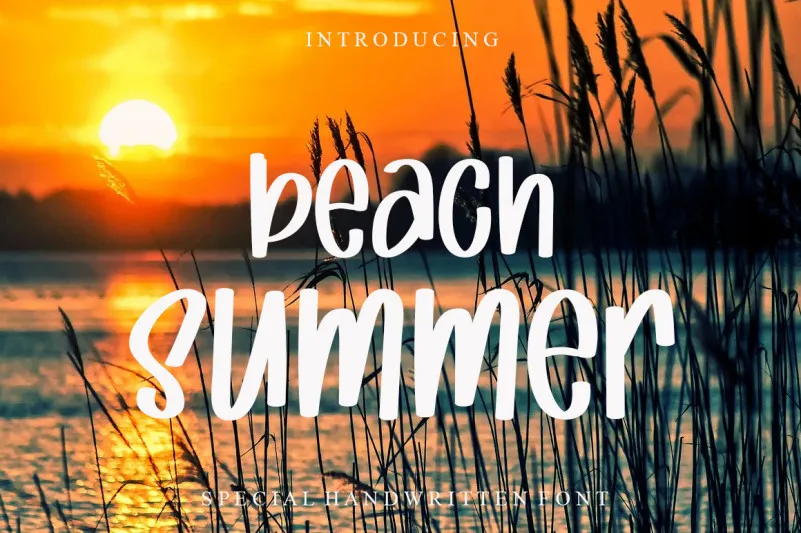
A Beach Summer Font é uma elegante fórmula de letra cursiva projetada para criar um ambiente divertido e inovador. Inspirada nos ensolarados dias da praia, essa fonte vai tornar seus trabalhos únicos e singulares. Ideal para designers que desejam dar um toque especial a suas criações digitais ou impressas, é perfeita para se tornar o principal aliado em projetos criativos. Seja na criação de cartões de visita, aplicativos ou qualquer outro projeto visual, esta fonte vai certamente fazer você cair amando. Experimente essa versão delicada e divertida que adora os dias quentes da praia, seja seu melhor companheiro para criar experiências memoráveis neste verão vibrante.